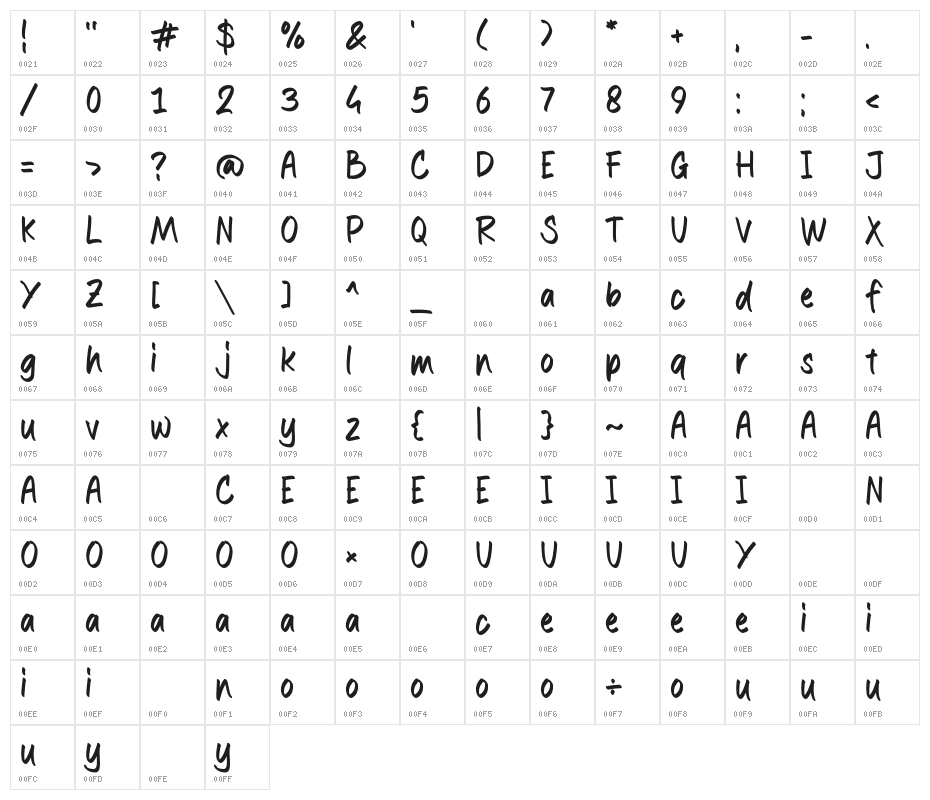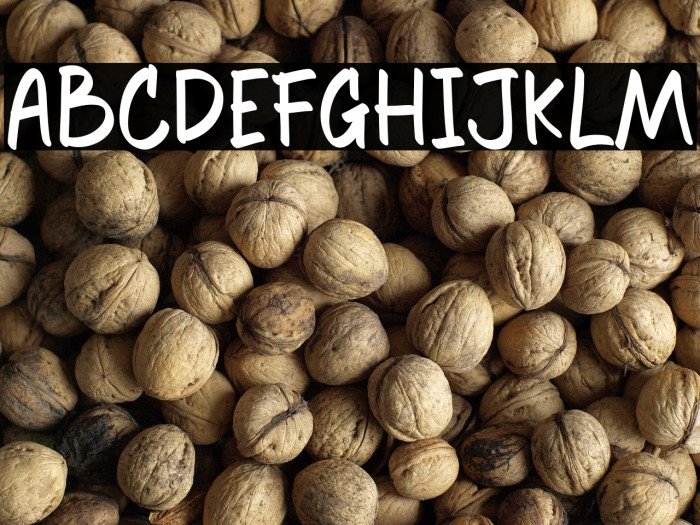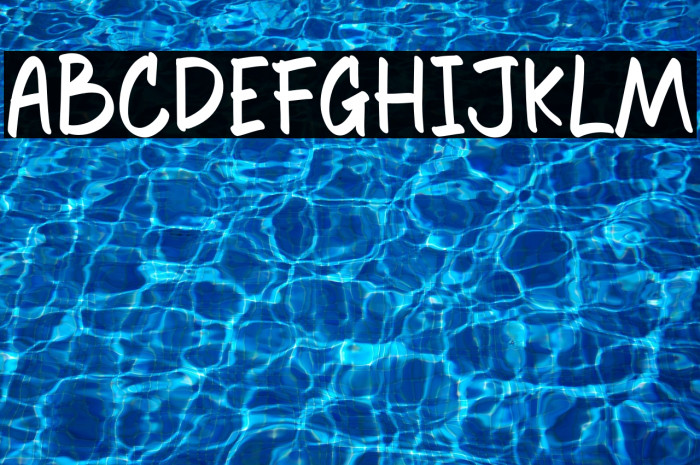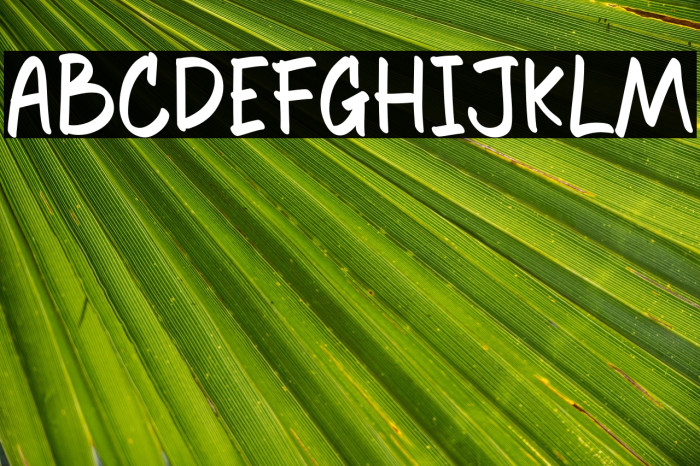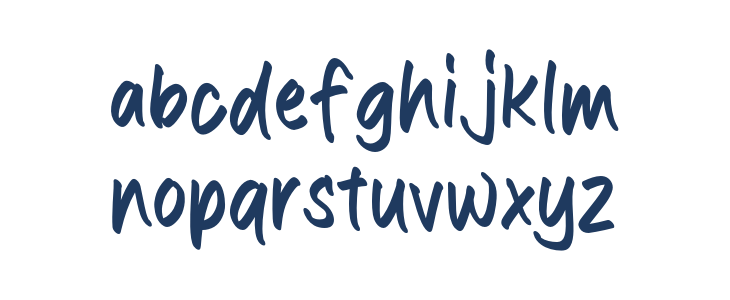
Hook Franco Font
| Stile generale | Playful, Energetic, Informal |
| Caso d'uso | Headlines, Creative projects, Personal branding |
| Progetti proposti | Ideal for greeting cards, children's books, creative posters, and personal branding. |